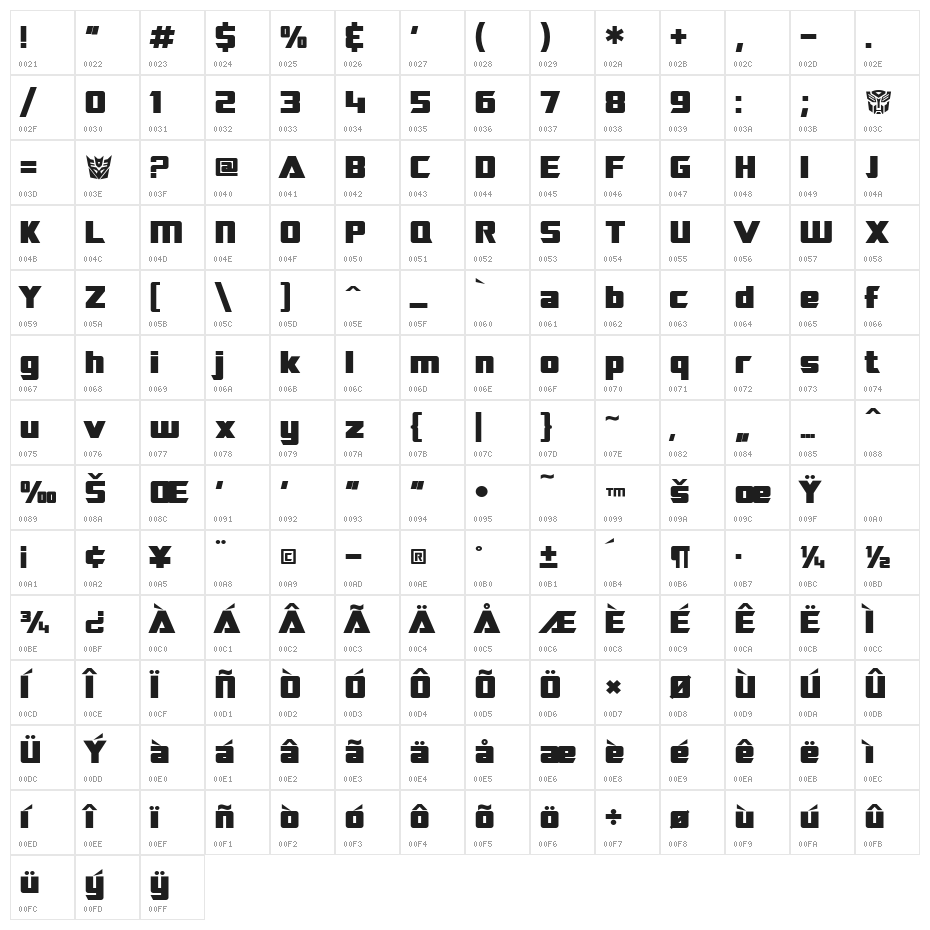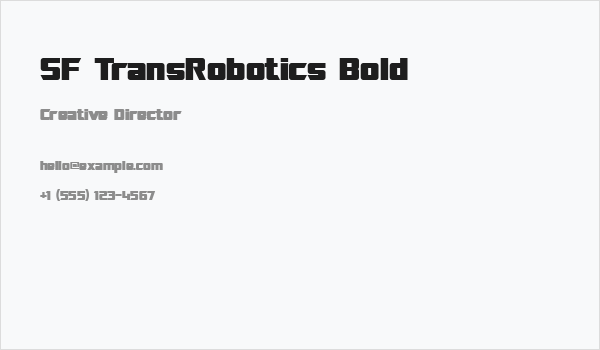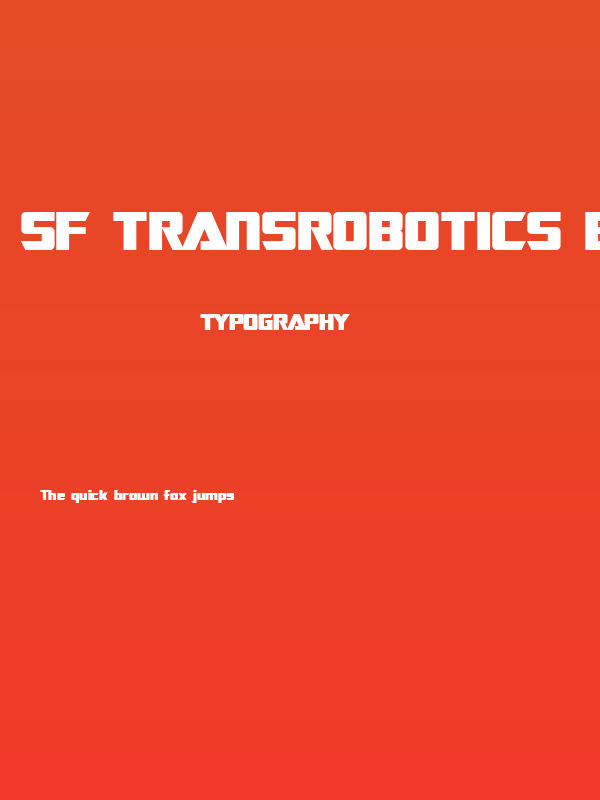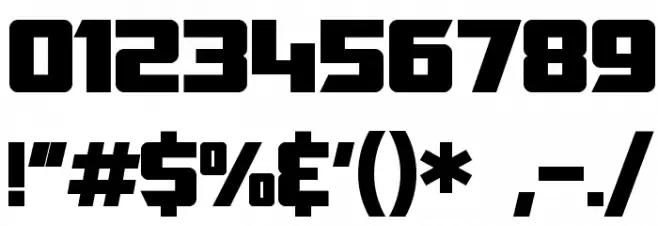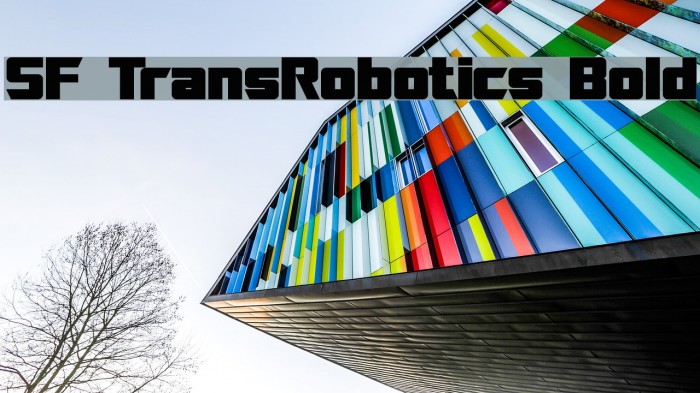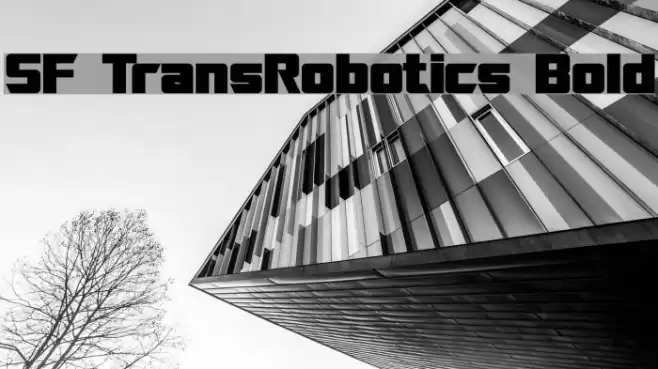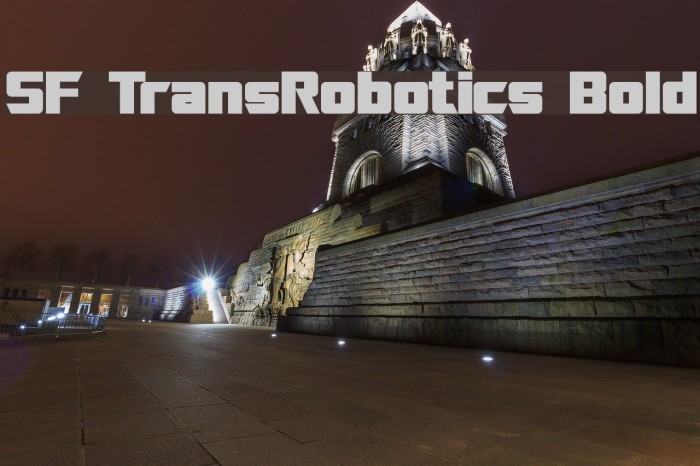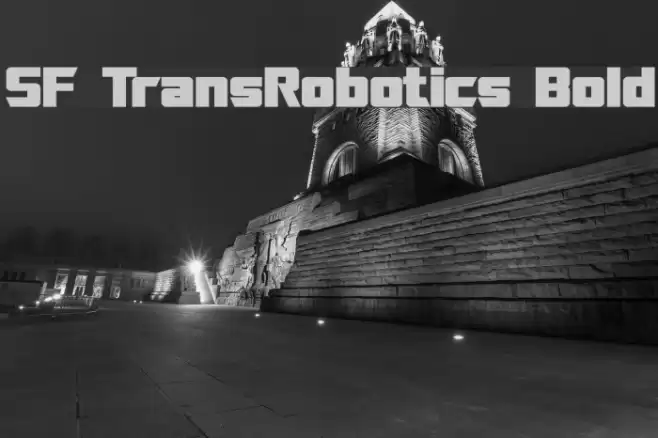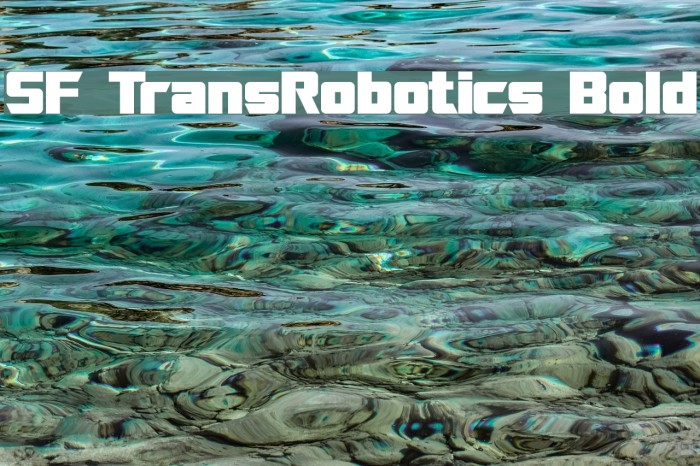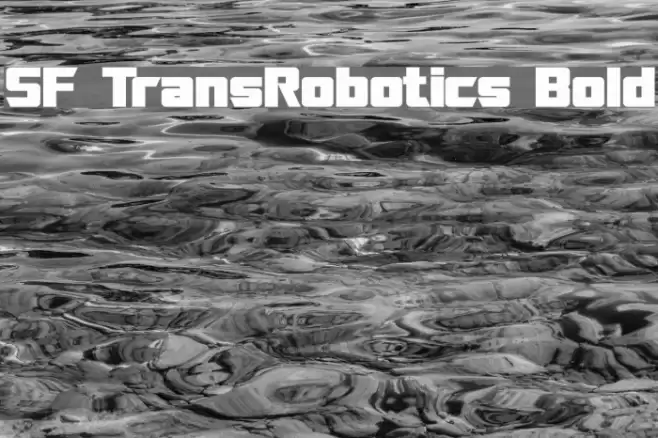
SF TransRobotics Bold Font
| مشاريع مقترحة | Ideal for technology branding, video game titles, sci-fi movie posters, and futuristic product packaging. |